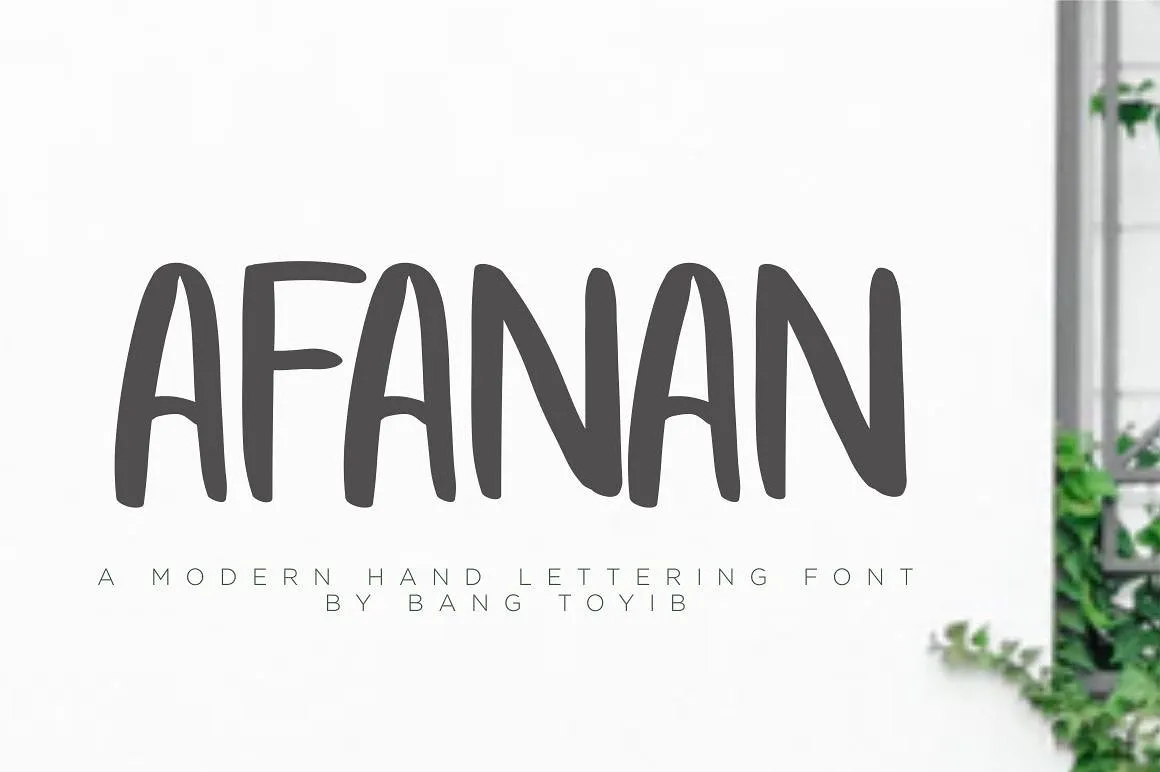
AFANAN Brush Font – Download Grátis
Olá amigos, apresentamos a vocês AFANAN, uma fonte de letra à mão moderna criada por Bang Toyib. AFANAN é um belo tipo de tração humana feito a mão com uma linha grossa perfeita para adicionar um toque de romance e encanto às suas criações. Este script se destaca especialmente como um tipo para exposição ou fonte de título, sendo perfeitamente adaptado para logotipos, nomes de marca, branding, roupas, capas de livros, posts no Instagram e outras aplicações. AFANAN é a escolha ideal para estilos modernos que valorizam o charme natural das letras à mão.